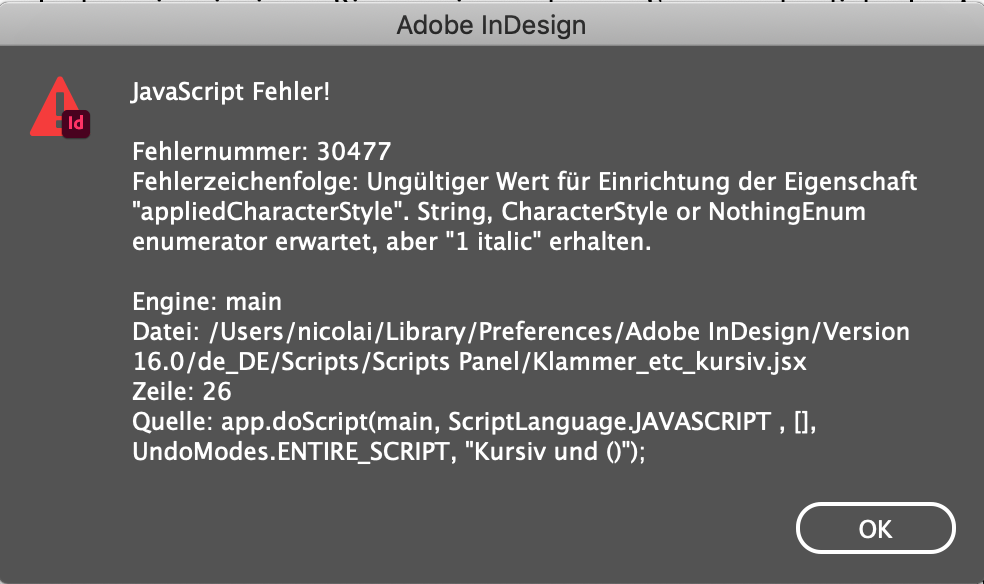
GREP-Suchen-Ersetzen: kursiver Text in rechte Klammern
Eine Frage an die GREP-Profis, zu der ich hier und andernorts nichts finden konnte und die mir schon länger Kopfzerbrechen bereitet:
Ich importiere meine Texte immer mit allen lokalen Formatierungen, suche diejenigen, die ich erhalten möchte und weise ihnen Zeichenformate zu, bevor ich alle Absatzformate zuweise und dabei noch vorhandene Abweichungen überschreibe.
Nun ist es eine verbreitete Unart, dass die Leute Klammern nicht mitkursivieren wenn der Klammerninhalt kursiv ist. Sie klicken wohl einfach doppelt auf das Wort, das kursiv werden soll, und dabei werden die Klammern eben nicht mitausgewählt. Sie wissen es entweder nicht besser oder sind zu faul, auch die Klammern kursiv zu setzen.
Die würde ich nun aber wahnsinnig gern kursiv setzen, weil recte Klammer vor/nach kursivem Text sieht einfach besch***en aus. Und es passieren Unfälle wie f) und ähnliche. Kennt ihr vielleicht. Das händisch durchzugehen schaffe ich aber leider nicht, das ist zu viel Text in der Summe.
Kennt da jemand eine Abhilfe mit GREP-Suchen-Ersetzen?
Das Problem ist, soweit ich sehe, dass man nicht zwei verschiedene Formatierungen in der Suche definieren kann, auch nicht mit Lookahead/-behind.
Wenn ich etwa
\([\l\u]
suche und bei Format ›kursiv‹ festlege, wird nur kursive Klammer + kursiver Text gefunden, nicht aber recte Klammer vor kursivem Text.
Mir wäre auch schon geholfen, wenn ich kursiven Text vor/nach Klammern (Format egal) finden könnte, dann könnte ich die Stellen händisch durchgehen. Aber auch wenn ich mit Lookbehind nach
(?<=\()[\l\u]
suche und bei Format kursiv einstelle, werden nur Stellen mit ebenfalls kursiven Klammern gefunden.
Heißt, ich kann kursive Klammern vor/nach kursivem Text finden, und ich kann recte Klammern vor/nach recte Text finden, aber nicht recte Klammern vor/nach kursivem Text oder kursiven Text vor/nach recte Klammern egal welchen Formats.
Klar könnte ich ohne Formatierung suchen und die Fundstellen alle händisch durchgehen und anpassen – aber es ist wirklich seeehr viel Text und das Problem habe ich bei so ziemlich jedem Buch, das ich setze.
Hat da jemand eine Idee oder vielleicht sogar eine Lösung?
Ich weiß nicht, um welcher Art Texte es sich handelt, aber es gibt Textarten, in denen es die Satzlogik bräche, die Klammern stets an den eingeklammerten Text anzugleichen (texttext (terminus technikus text) texttext) . Insofern würde ich der händischen Überprüfung den Vorrang geben.
Danke für die Antwort. Es sind wissenschaftliche Texte. Die Stellen würde ich schon händisch durchgehen wollen, ich will nur die vielen Stellen herausfiltern, wo recte Klammer und recte Text beieinander stehen, dass ich diese nicht alle durchklicken muss.
P.S.: Die Diskussion wollte ich absichtlich nicht aufmachen, wo Klammern kursiv sein sollen oder nicht. 😅
Ich sehe es aber ähnlich wie du, denke ich:
Text text text (text text Text) text Text
Text text text (text text Text) text Text [hier würde ich ggf. händisch das Kerning anpassen, wenn die Stellen easy finde]
aber
Text text text (text text Text) text Text
— aber lass uns das hier ausklammern
Ich musste etwas herumprobieren und habe dann herausgefunden, dass ich im Skript "1 italic" (Zeile 48) durch den Namen meines gewünschten Italic-Zeichenformats ersetzen muss (für alle, die es noch interessiert). Sonst bekomme ich die im Bild gezeigte Fehlermeldung.
Wenn ich das Skript dann laufen lasse, wird den Klammern (und vermutlich auch den anderen definierten Zeichen) mein Italic-ZF zugewiesen, wenn danach oder davor Italic vorliegt. Soweit ich sehe, macht es also, was es soll!
Ich habe nur leider keine Möglichkeit, die Fundstellen manuell durchzugehen und zu bestätigen oder abzulehnen und vor dem Weitersuchen händische Kerning-Anpassungen vorzunehmen. Wie oben an Phoibos geschrieben, würde ich nämlich bei:
Text text (text Text text) Text text
die Klammer nicht kursiv setzen. Macht das Skript aber.
Das ist schon mal eine gute Grundlage. Aber mir fehlt da die Kontrolle, was geändert wird und was nicht.
Nun kenne ich mich mit Skripten nicht wirklich aus. Weiß jemand, ob man es so anpassen könnte, dass man die Fundstellen einzeln bestätigt? Dann würde ich mich da mal einlesen. (Oder weiß jemand vielleicht sogar schon, was man ändern müsste?)
ich gehe den Text einzeln durch.
Wenn ich eine Fundstelle gefunden habe, setze ich den Curser rein und aktiviere das Script mit einem Shortcut.
ich gehe den Text einzeln durch.
Meinst du mit einer generellen Suche nach den Klammern (und anderen Zeichen) ohne Formateinstellungen?
wenn ich die anderen 'wichtigen' Dinge erledigt habe - wie Absatz- und Zeichenformate. Außerdem hat das Zeichenformat 'Italic' eine Farbe, damit ich es schneller finden kann.
Ich glaube, ich muss mir einfach mal Zeit nehmen mich ins Skripten einzulesen.